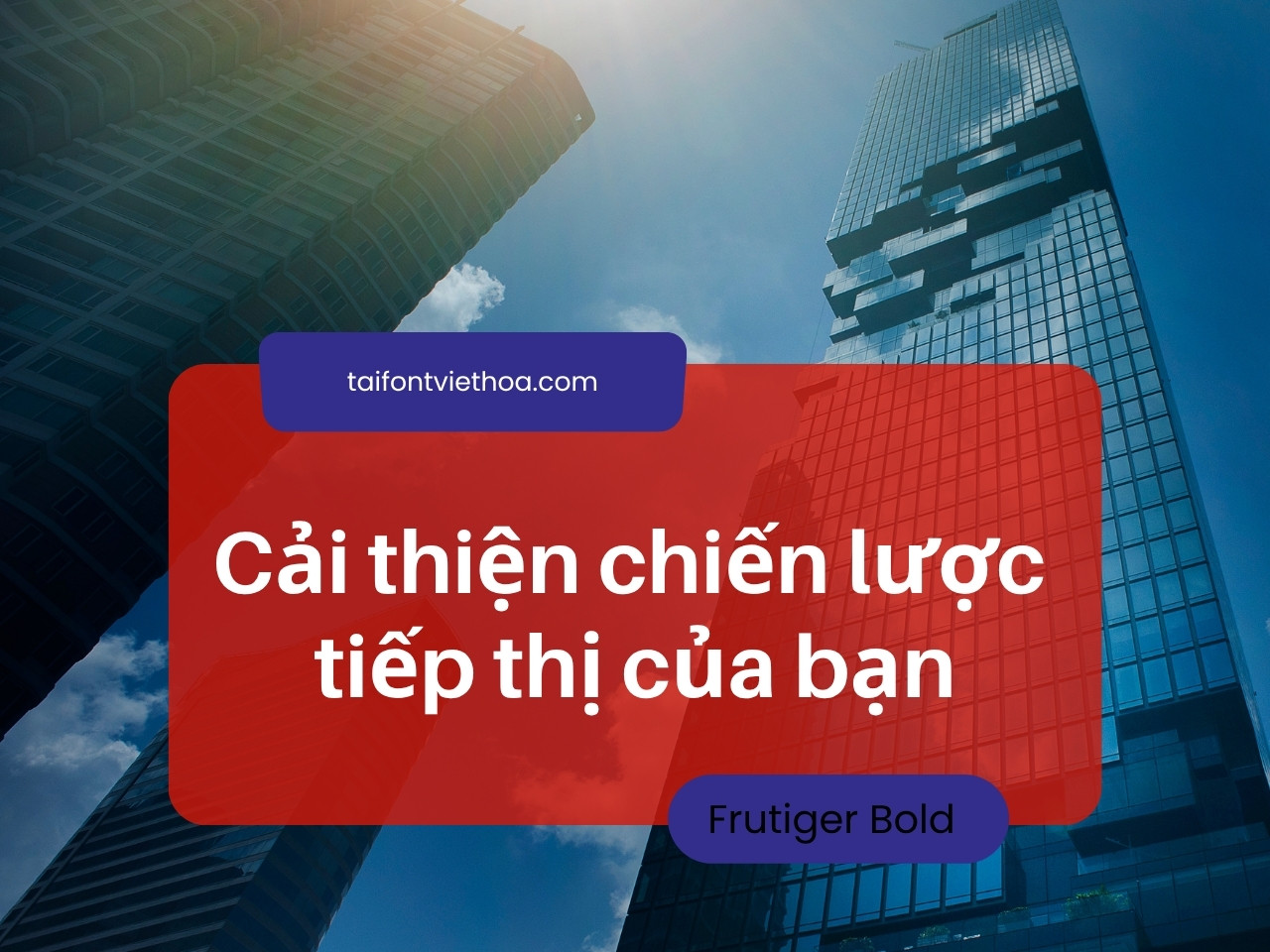
Font việt hóa Frutiger Bold
Tác giả Font: Lưu Hà An
Giới thiệu font Frutiger Bold – Di sản chữ hiện đại của Adrian Frutiger
Frutiger Bold là một trong những biến thể nổi bật của bộ font Frutiger – hệ chữ sans-serif huyền thoại do nhà thiết kế Thụy Sĩ Adrian Frutiger phát triển vào đầu thập niên 1970. Ban đầu được thiết kế cho sân bay Charles de Gaulle ở Paris, Frutiger nhanh chóng trở thành một trong những kiểu chữ được sử dụng rộng rãi nhất trong thế giới in ấn và hiển thị số nhờ sự rõ ràng, dễ đọc và tính ứng dụng cao. Phiên bản Việt hóa của Frutiger Bold do Luuhaan2008Roblox thực hiện, hỗ trợ đầy đủ tiếng Việt cùng hơn 150 ngôn ngữ toàn cầu. Bộ font này đã được taifontviethoa.com chọn lọc và chia sẻ, nhằm phục vụ cộng đồng thiết kế trong các dự án cần trình bày thông tin rõ ràng, hiệu quả và mang tính thương hiệu chuyên nghiệp.
Đặc điểm kỹ thuật mạnh mẽ và ứng dụng thực tiễn của Frutiger Bold
Frutiger Bold mang phong cách sans-serif hiện đại, với độ đậm cao, đường nét chắc chắn, ổn định và khoảng cách giữa các ký tự được tối ưu cho khả năng đọc từ xa. Thiết kế font giữ cấu trúc hình học đơn giản nhưng giàu tính hệ thống, tạo nên sự rõ ràng và gợi cảm giác tin cậy. Font phù hợp cho tiêu đề, logo, biển hiệu, giao diện UI/UX, bảng chỉ dẫn, tài liệu kỹ thuật và các thiết kế nhận diện thương hiệu. Frutiger Bold đặc biệt phù hợp với các ngành như công nghệ, giáo dục, y tế, bất động sản, truyền thông kỹ thuật số và thiết kế sản phẩm hướng tới sự minh bạch, chuyên nghiệp và hiệu quả thị giác cao.